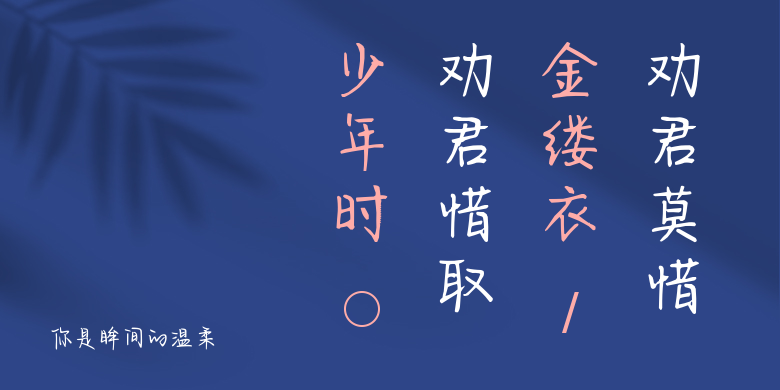
你是眸间的温柔
你是眸间的温柔,这款字体结构工整、笔画清晰,兼顾美观与易读性,适用于标题、正文、海报、包装、LOGO 等多种场景。字形优雅稳定,风格百搭耐看,适配日常排版与创意设计,让文字呈现更舒适、更具质感。你是眸间的温柔一笔一画,皆是细节,以均衡的比例、流畅的线条打造舒适视觉体验,字形端正大气,风格简约现代。无论是商业设计、品牌宣传还是日常排版,都能轻松驾驭,让文字更有格调与力量。你是眸间的温柔字体下载。